Font chữ không chân, còn gọi là Sans Serif, từ lâu đã trở thành lựa chọn hàng đầu của nhiều nhà thiết kế nhờ vẻ đẹp hiện đại, tối giản và dễ đọc. Cho dù bạn đang tìm kiếm những mẫu font không chân miễn phí, font Việt hóa hay các kiểu chữ hiện đại phục vụ thiết kế sáng tạo, việc lựa chọn font phù hợp vẫn luôn là yếu tố quan trọng giúp nâng tầm sản phẩm của bạn. Bài viết dưới đây sẽ tổng hợp những font chữ không chân đẹp, nổi bật cùng các nguồn tải miễn phí, giúp bạn dễ dàng tham khảo và sử dụng cho dự án của mình.
Font chữ không chân, hay còn gọi là sans-serif, đã trở thành lựa chọn phổ biến trong thiết kế đồ họa và văn bản hiện đại. Với đặc điểm không có chân chữ, những font này mang lại cảm giác tối giản, hiện đại và dễ đọc. Một số cái tên tiêu biểu được ưa chuộng hiện nay là Helvetica Now, Futura, Arial và Calibri. Đặc biệt, Open Sans đã nổi bật nhờ sự thân thiện và dễ dàng khi sử dụng trong các tài liệu và trang web.
Ngoài ra, các font chữ Việt hóa như Quicksand, Proxima Nova hay Montserrat cũng rất được yêu thích. Chúng không chỉ thể hiện sự tinh tế trong thiết kế mà còn phù hợp cho nhiều mục đích sử dụng khác nhau, từ logo thương hiệu cho đến báo cáo, bài thuyết trình. Việc lựa chọn một font chữ không chân đẹp và hiện đại sẽ giúp nâng cao tính thẩm mỹ và sự chuyên nghiệp cho các sản phẩm truyền thông.
Với sự đa dạng và phong phú của các font chữ không chân, bạn hoàn toàn có thể tìm thấy kiểu chữ phù hợp với phong cách và thông điệp bạn muốn truyền tải. Hãy thử nghiệm và tìm ra font chữ mà bạn yêu thích nhất!
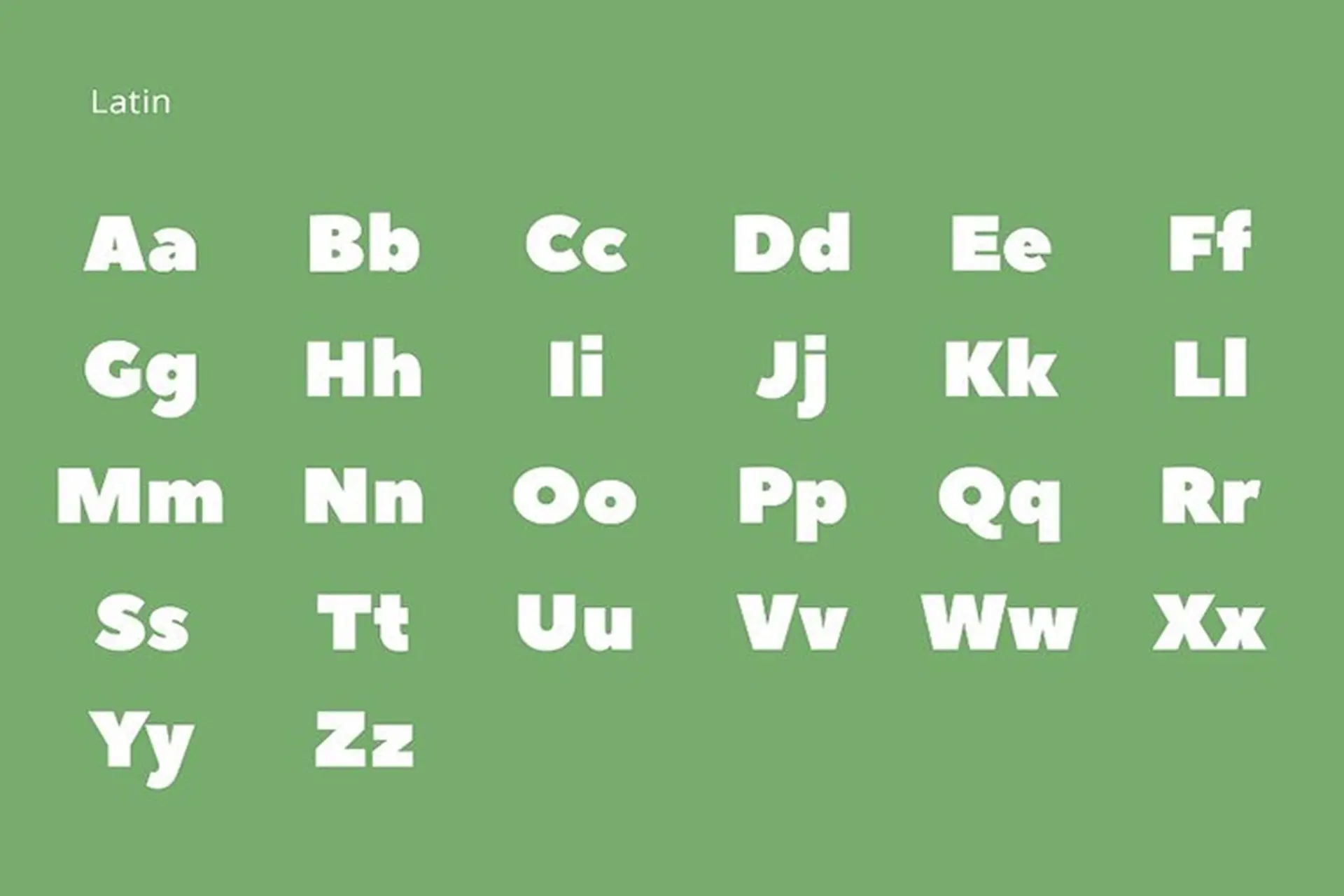
Font chữ không chân, hay còn gọi là sans-serif, ngày càng trở thành lựa chọn phổ biến trong thiết kế đồ họa và truyền thông. Những font chữ này thường mang đến cảm giác hiện đại, sạch sẽ và dễ đọc. Trong số những font chữ không chân đẹp và được Việt hóa, các tên tuổi như Helvetica Now, Futura, và Roboto chắc chắn không thể bỏ qua.
Nếu bạn đang tìm kiếm font chữ thú vị để sử dụng cho dự án của mình, có rất nhiều lựa chọn miễn phí mà bạn có thể tải xuống từ các website chuyên cung cấp font chữ. Chẳng hạn, Open Sans và Quicksand đều là những cái tên nổi bật, được thành viên cộng đồng sáng tạo đăng tải và chia sẻ.
Ngoài ra, còn có nhiều font chữ mới mẻ như Proxima Nova hay Peace Sans, rất phù hợp cho các thiết kế logo hay thương hiệu. Với sự đa dạng này, chắc chắn bạn sẽ tìm thấy font chữ ưng ý, đồng thời giúp nâng tầm cho những sản phẩm của mình mà không cần phải lo lắng về chi phí. Hãy thử nghiệm và khám phá các font chữ không chân này nhé!
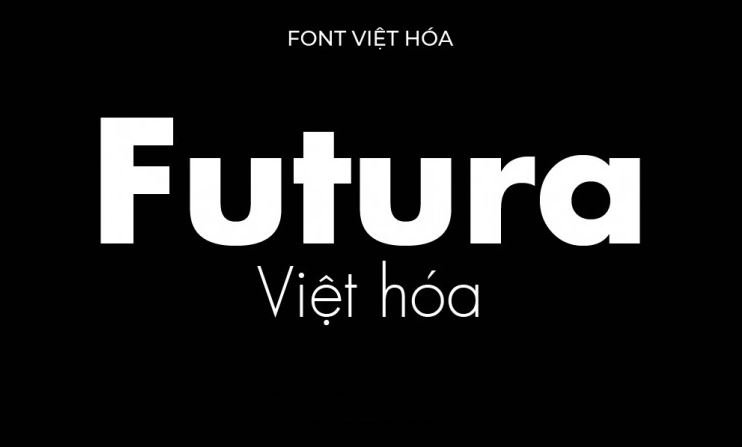
Font chữ không chân, hay còn gọi là sans serif, đang chiếm ưu thế trong thiết kế hiện đại nhờ vào sự rõ ràng và dễ đọc của chúng. Nổi bật nhất trong danh sách này là Helvetica Now và Futura, những font chữ đã tạo nên xu hướng thiết kế từ thập niên 1920 và vẫn giữ được sức hút cho đến ngày nay. Chúng thường được lựa chọn cho thương hiệu, trang web vì khả năng truyền tải thông điệp một cách hiệu quả.
Ngoài ra, các font như Roboto, Open Sans và Quicksand cũng là những lựa chọn tuyệt vời cho những ai yêu thích sự đơn giản nhưng hiện đại. Những nét chữ thanh mảnh, tối giản giúp tạo nên vẻ đẹp sang trọng, tinh tế cho các sản phẩm. Hơn nữa, với sự phổ biến của font chữ không chân tại Việt Nam, nhiều font đã được Việt hóa như SVN Gotham hay UTM Avo, đảm bảo rằng người dùng có thể thoải mái thể hiện ý tưởng của mình bằng chữ viết thuần Việt.
Đặc biệt, Montserrat và Lato không chỉ nổi bật mà còn rất linh hoạt, phù hợp cho cả in ấn lẫn thiết kế số. Với sự phát triển liên tục của nghệ thuật thiết kế, việc lựa chọn font chữ không chân sẽ mang đến cho bạn những cơ hội sáng tạo bất tận.
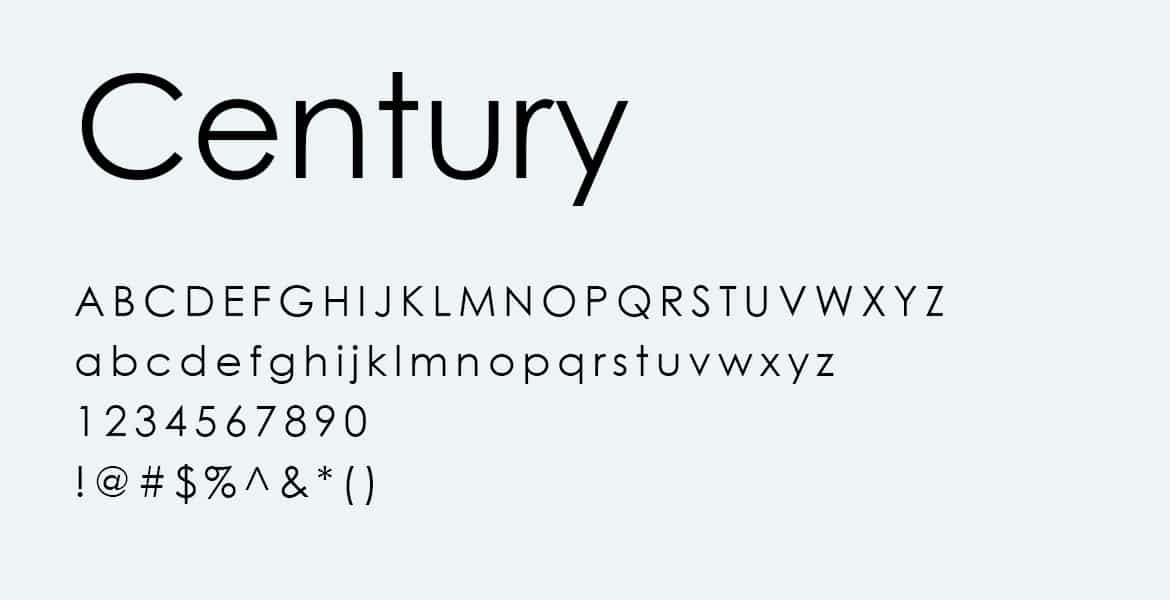
Trong thiết kế đồ họa hiện đại, việc lựa chọn font chữ không chân (sans serif) đóng vai trò rất quan trọng, không chỉ vì tính thẩm mỹ mà còn vì tính dễ đọc. Một trong những cái tên nổi bật trong danh sách này là Helvetica Now, với độ rõ nét và sự tối giản giúp nổi bật thông điệp cần truyền tải. Tiếp theo là Futura, một phông chữ ra đời từ năm 1927, nổi bật với hình dáng hình học và sự hiện đại.
Ngoài ra, Roboto và Open Sans cũng là những lựa chọn tuyệt vời cho các dự án hàng ngày. Roboto mang đến cảm giác hiện đại và thân thiện, trong khi Open Sans lại thể hiện sự rõ ràng và dễ đọc, là lý do nó được sử dụng rộng rãi trong nhiều loại thiết kế khác nhau.
Bên cạnh đó, Proxima Nova và Montserrat cũng nằm trong danh sách những font chữ không chân phổ biến. Chúng không chỉ phù hợp cho tiêu đề mà còn rất tiện dụng cho nội dung. Những font này đều phản ánh xu hướng hiện đại, giúp cho mọi thiết kế trở nên hấp dẫn và chuyên nghiệp hơn. Nếu bạn đang tìm kiếm font chữ cho các thiết kế của mình, hãy thử nghiệm với các phông chữ này để tìm ra sự kết hợp hoàn hảo nhất!
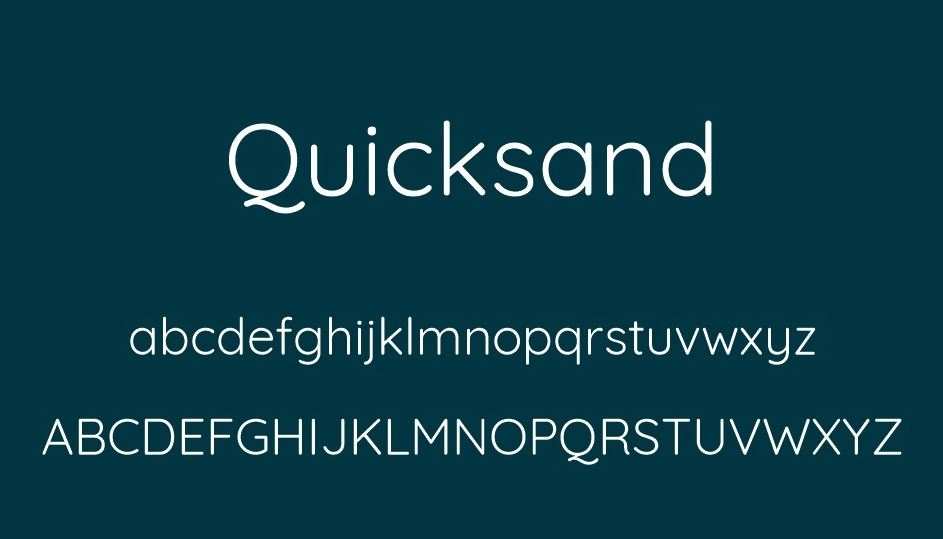
Nếu bạn đang tìm kiếm những font chữ không chân đẹp và miễn phí, thì bạn đã đến đúng chỗ! Các font chữ không chân, hay còn gọi là sans serif, nổi bật với đường nét thanh mảnh, rõ ràng, không có các chi tiết thừa, giúp nâng cao độ dễ đọc. Điều này rất quan trọng trong thiết kế đồ họa cũng như khi bạn tạo nội dung số.
Trên nhiều website, bạn có thể thoải mái tải về những bộ font chữ không chân ấn tượng, từ những nguồn do cộng đồng chia sẻ. Một số cái tên nổi bật trong danh sách top font chữ không chân Việt hóa hiện nay có thể kể đến như TH-Sink, TH-Roma và các font quen thuộc như Open Sans, Roboto hay Helvetica. Những font này không chỉ phù hợp cho thiết kế logo mà còn rất hữu dụng trong các tài liệu, bài thuyết trình, hay thậm chí là blog.
Để tải font về máy, bạn chỉ cần vài bước đơn giản. Sau khi hạ tải, bạn giải nén thư mục, chọn font và nhấp chuột phải để cài đặt. Như vậy, bạn đã sẵn sàng làm mới không gian sáng tạo của mình với những font chữ đẹp mắt này!
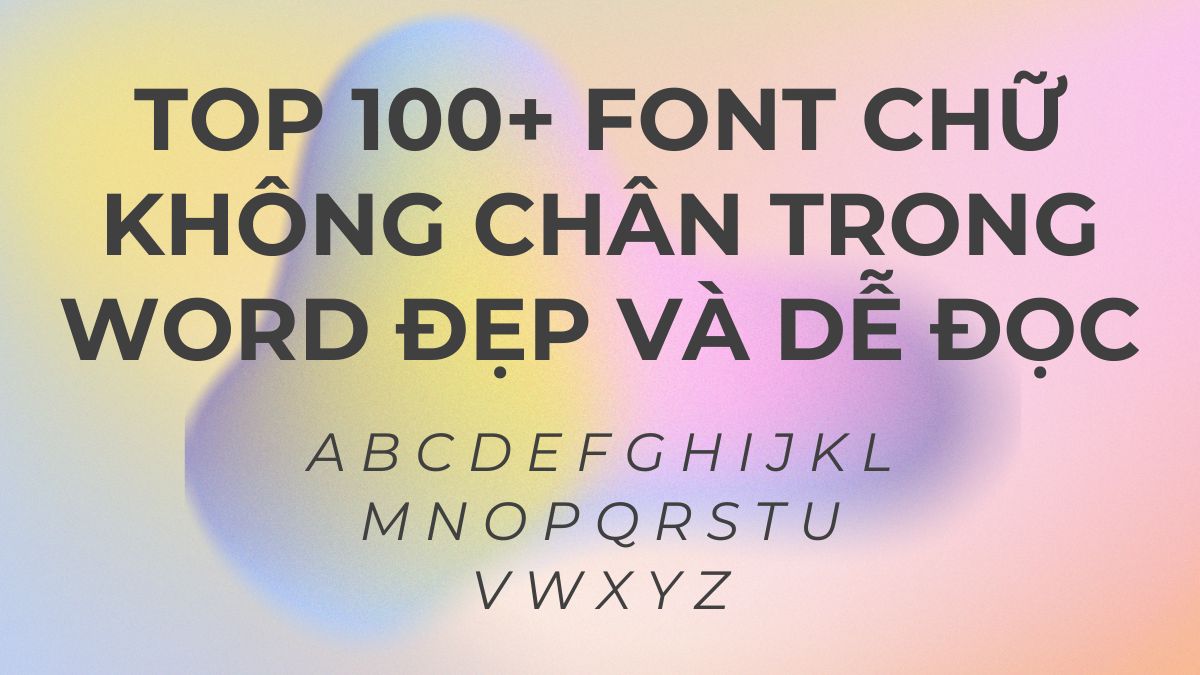
Bộ 3 Font NVN January Tiếng Việt, do Design by Font Việt Hóa NVN thiết kế, mang đến cho người dùng sự lựa chọn thú vị với những font chữ không chân đẹp và hiện đại. Các font này không chỉ giúp nâng cao tính thẩm mỹ cho các thiết kế mà còn phù hợp với việc sử dụng trong nhiều lĩnh vực khác nhau, từ quảng cáo đến truyền thông.
Trong một thế giới thiết kế ngày càng phát triển, việc chọn lựa một kiểu chữ phù hợp là rất quan trọng. Những font như Helvetica Now hay Futura không chỉ nổi bật với sự tinh tế mà còn được các thương hiệu lớn yêu thích. Thêm vào đó, việc Việt hóa những font chữ này giúp chúng trở nên gần gũi và dễ tiếp cận hơn với người dùng Việt Nam.
Chúng ta có thể dễ dàng tìm thấy nhiều mẫu font không chân Việt hóa đẹp mắt, chẳng hạn như Quicksand hay Open Sans. Các font này không chỉ có khả năng hiển thị tốt mà còn mang lại cảm giác dễ đọc, thân thiện. Với sự đa dạng trong phong cách và ứng dụng, những font chữ này thực sự là lựa chọn lý tưởng cho mọi thiết kế sáng tạo.
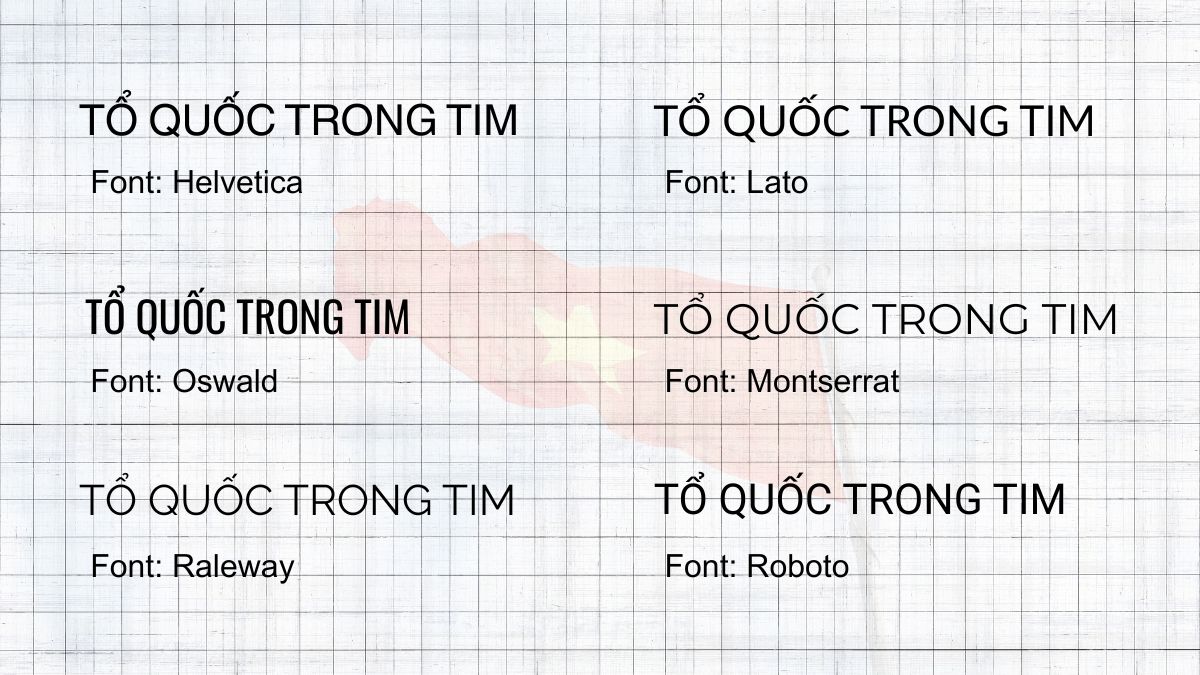
Font chữ không chân (sans serif) đang ngày càng trở nên phổ biến trong thiết kế hiện đại nhờ sự thanh lịch và dễ đọc. Trong số những font đẹp nhất hiện nay, chúng ta không thể không nhắc đến Helvetica Now, với đường nét tinh tế, cùng Proxima Nova và Futura, nổi bật với thiết kế hiện đại, mang đến cảm giác chuyên nghiệp và năng động.
Ngoài ra, font Arial và Calibri cũng được yêu thích vì tính ứng dụng cao trong nhiều tài liệu. Đặc biệt, Open Sans là lựa chọn lý tưởng cho các trang web nhờ giao diện rõ ràng, dễ đọc. Quicksand hay Raleway cũng là những cái tên nổi bật với phong cách tân tiến, thích hợp cho việc tạo logo và nhận diện thương hiệu.
Tính linh hoạt của các font chữ không chân như Work Sans và Noto Sans cũng giúp chúng có thể được áp dụng rộng rãi trong nhiều lĩnh vực khác nhau. Với số lượng font không chân phong phú, việc lựa chọn một kiểu chữ phù hợp thật sự là một thử thách thú vị cho những ai yêu thích thiết kế.
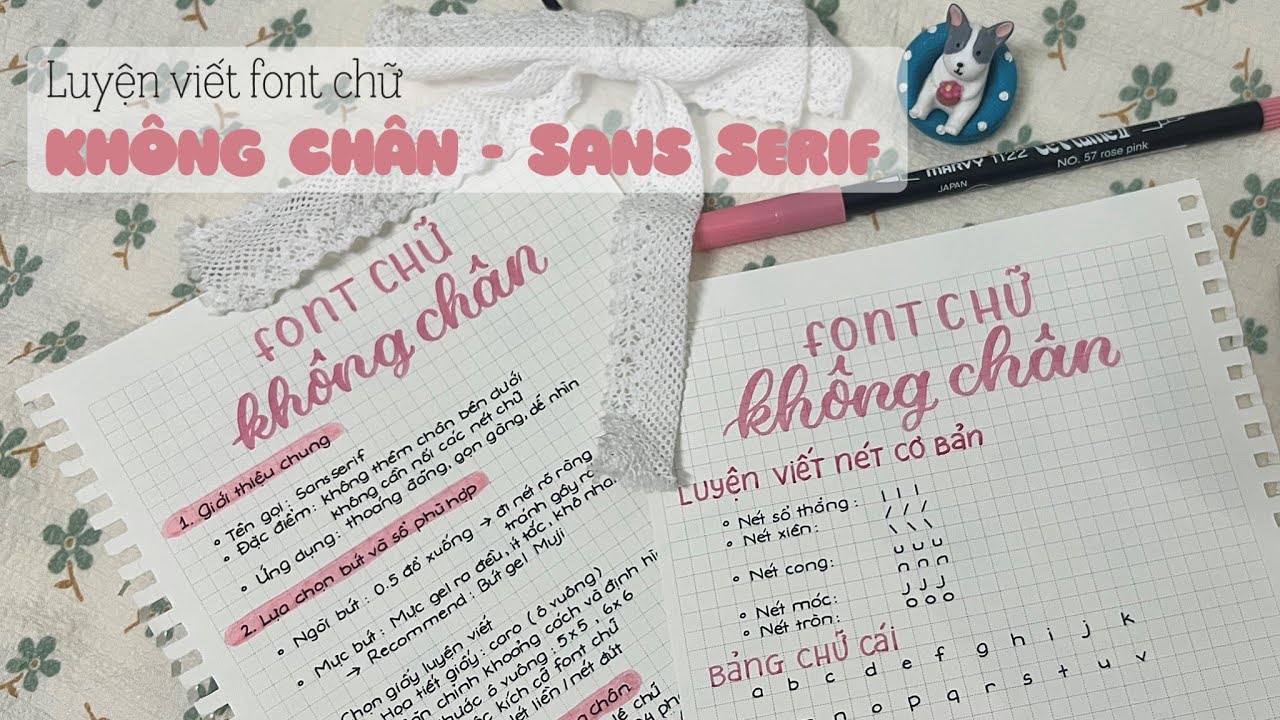
Font chữ không chân, hay còn gọi là sans serif, hiện đang trở thành một trong những lựa chọn yêu thích của các designer trong việc tạo ra các ấn phẩm mang tính thẩm mỹ cao. Sự giản dị, hiện đại của các phông chữ này mang lại nét trẻ trung và sáng tạo, giúp các tác phẩm truyền tải thông điệp một cách rõ ràng, dễ hiểu.
Trong số những phông chữ được ưa chuộng, Coco nổi bật với vẻ đẹp thanh lịch, thường được sử dụng cho các logo thời trang sang trọng. Hay như Raleway, với phong cách tân grotesque, đã chiếm cảm tình của nhiều nhà thiết kế nhờ vào sự tinh tế và tính thẩm mỹ vượt trội.
Ngoài ra, chúng ta không thể không nhắc đến Montserrat, Lato và Open Sans—những font chữ rất dễ đọc, lý tưởng cho công việc hàng ngày và thiết kế kỹ thuật số. Những lựa chọn này không chỉ đẹp mắt mà còn phù hợp với nhiều loại dự án, từ quảng cáo đến bản in. Việc sử dụng font chữ sans serif chắc chắn sẽ đem lại cho thiết kế của bạn một làn gió mới, nổi bật và ấn tượng.
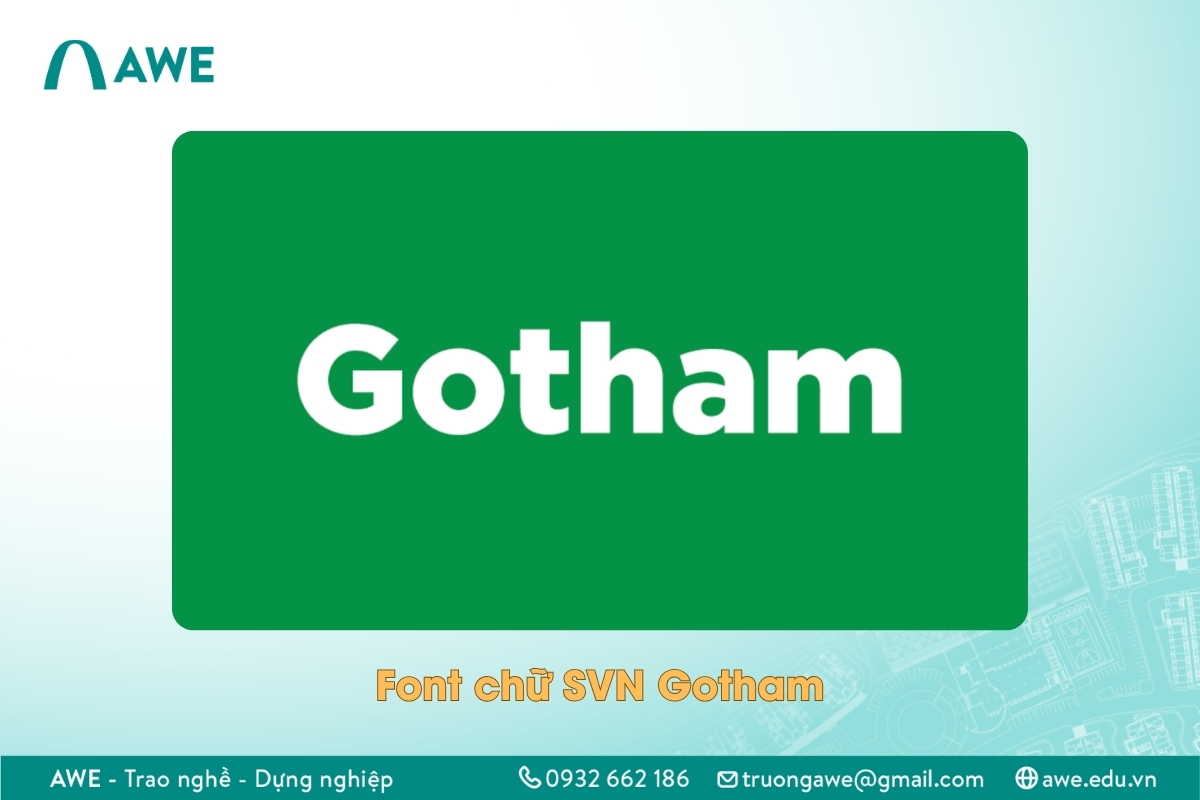
Phông chữ sans serif luôn được yêu thích trong lĩnh vực thiết kế nhờ vào sự hiện đại, gọn gàng và dễ đọc. Trong số những phông chữ nổi bật, Helvetica Now và Futura là những cái tên không thể không nhắc đến. Chúng không chỉ mang đến vẻ đẹp đơn giản mà còn nhìn gần gũi và dễ gây ấn tượng với người dùng. Helvetica Now, với thiết kế tinh tế, thường được lựa chọn cho các dự án thương hiệu hay giao diện người dùng vì tính dễ đọc và sự linh hoạt của nó.
Ngoài ra, mà còn phải kể đến Proxima Nova và Open Sans, những phông chữ này cũng rất phổ biến trong thiết kế web nhờ sự thích ứng tốt trên nhiều thiết bị khác nhau. Proxima Nova, với phong cách tân cổ điển, thường tạo ra vẻ đẹp thanh lịch, trong khi Open Sans mang lại cảm giác thân thiện và gần gũi.
Có những phông chữ sans serif khác như Raleway hay Simplifica cũng nổi bật không kém. Raleway mang đến sự thanh lịch, còn Simplifica lại ghi điểm với thiết kế đồng nhất và dễ dàng nhận diện. Những lựa chọn này thật sự làm phong phú thêm kho tàng phông chữ cho các nhà thiết kế.
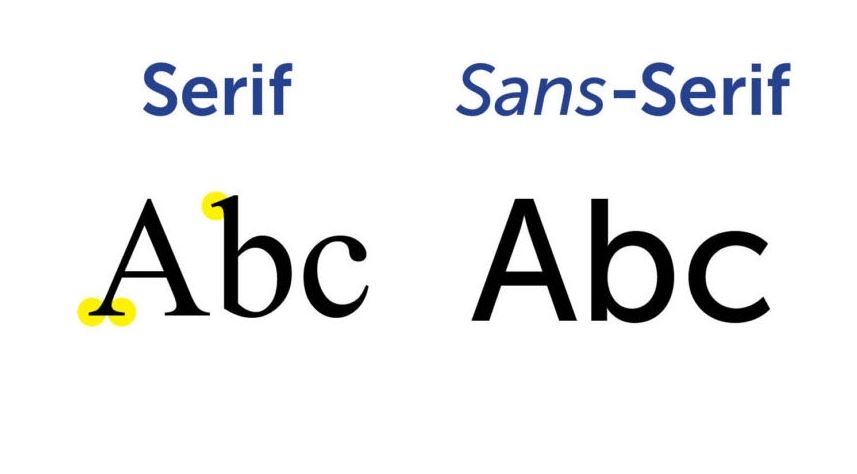
Font sans serif là một lựa chọn tuyệt vời cho các thiết kế hiện đại vì tính gọn gàng và dễ đọc của nó. Đặc biệt, các font chữ không chân như Open Sans hay Cabin mang lại cảm giác thân thiện và gần gũi, rất phù hợp cho các ứng dụng UI/UX, tài liệu số, hay banner quảng cáo. Với đường nét sạch sẽ và rõ ràng, chúng giúp người dùng tập trung hơn vào nội dung.
Một ưu điểm lớn của các font sans serif này là sự đa dạng về weight và width. Bạn có thể linh hoạt lựa chọn các kiểu chữ khác nhau như Gotham Thin, Medium, hay Ultra để xây dựng hệ thống nhận diện thương hiệu một cách đồng nhất và ấn tượng. Ngoài ra, các font được Việt hóa như 1FTV VIP DINKO hay 1FTV VIP Holly Days cũng mở rộng thêm sự lựa chọn cho các nhà thiết kế yêu thích văn phong Việt Nam.
Chất lượng hiển thị trên màn hình của các font sans serif cũng rất tốt. Với tỷ lệ cân đối và kiểu dáng hiện đại, chúng giúp người đọc dễ dàng tiếp cận mà không bị căng thẳng. Nếu bạn đang tìm kiếm một font chữ đẹp, dễ sử dụng cho dự án của mình, đừng ngần ngại thử nghiệm các font không chân Việt hóa!
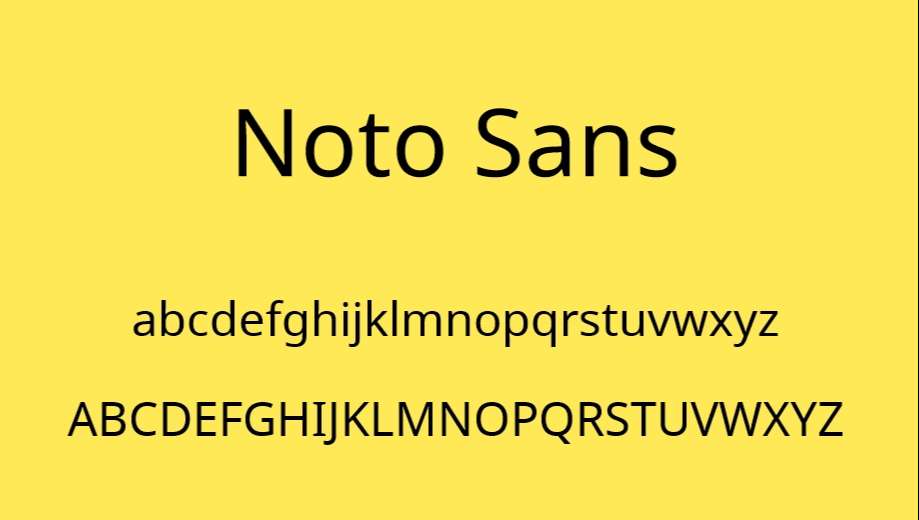
Tóm lại, việc lựa chọn phong cách viết và sử dụng ngôn ngữ phù hợp không chỉ giúp bài viết trở nên hấp dẫn hơn mà còn thể hiện được rõ ràng ý tưởng, thông điệp mà người viết muốn truyền tải. Qua việc áp dụng những cấu trúc và kỹ thuật viết này, chúng ta không chỉ nâng cao khả năng giao tiếp mà còn tạo ra những tác phẩm mang tính nghệ thuật và sức cuốn hút riêng. Hy vọng rằng những chia sẻ trong bài viết sẽ giúp bạn có thêm nhiều ý tưởng và cảm hứng để xây dựng những tác phẩm độc đáo và ý nghĩa trong tương lai.